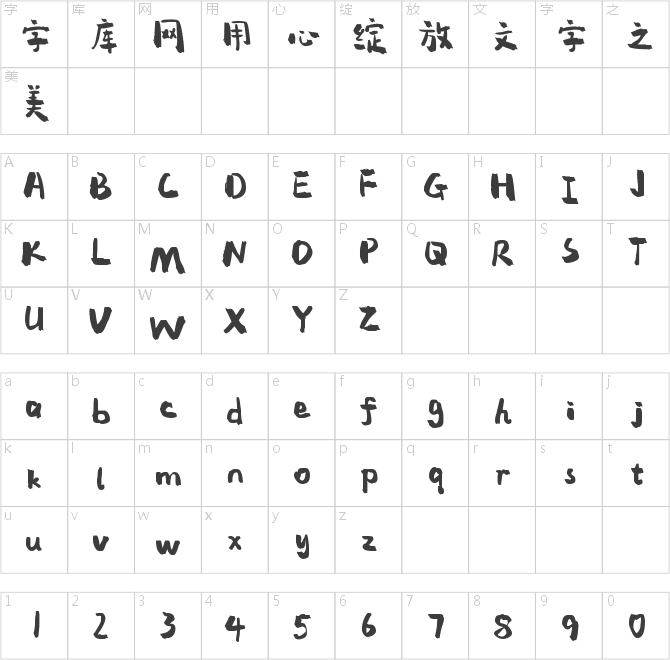
字魂101號(hào)-小確幸 詳情頁
字魂101號(hào)-
字魂101號(hào)-小確幸字體字庫是一款讓人賞心悅目、百看不厭的中文字體,適合各類廣告和產(chǎn)品包裝設(shè)計(jì)應(yīng)用,字體大小14.31MB,格式為ttf字體,上傳用戶是82年的拉菲,作者/版權(quán)方為字魂